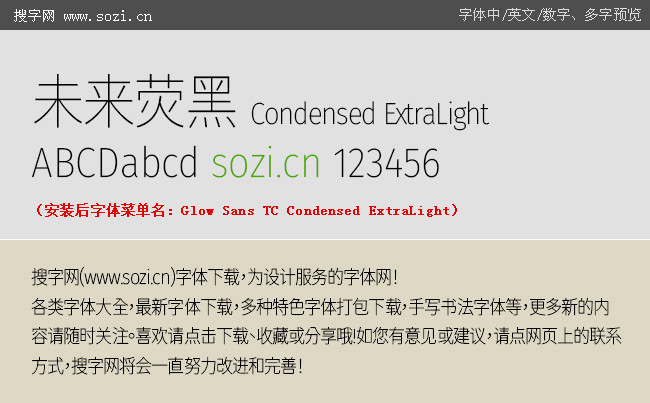
未來熒黑GlowSansTC-Condensed-ExtraLight
搜字網給大家提供一款未來熒黑GlowSansTC-Condensed-ExtraLight中文字體下載,未來熒黑GlowSansTC-Condensed版是未來熒黑中的一個瘦長體系列,未來熒黑是一個基于思源黑體、Fira Sans和Raleway的開源字體項目,該字體由八種字重,字體中宮與字面更加收斂,細節上面處理更加的干練,適合應用于藝術設計、平面宣傳設計、網頁設計等廣告設計。